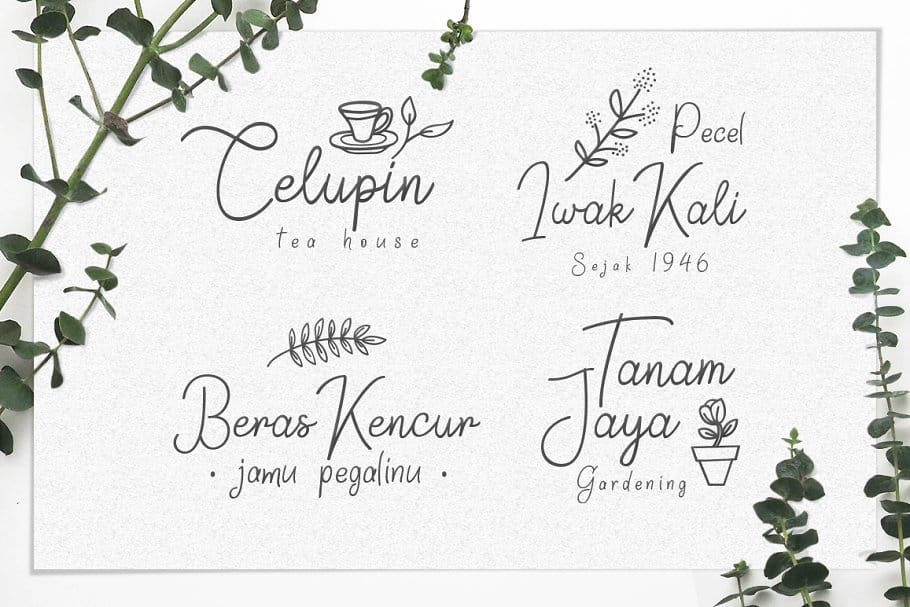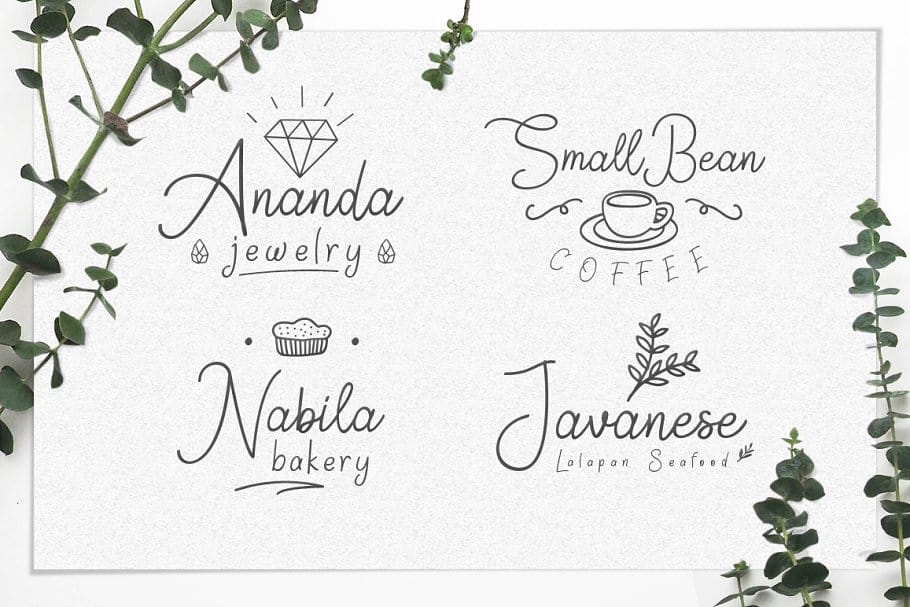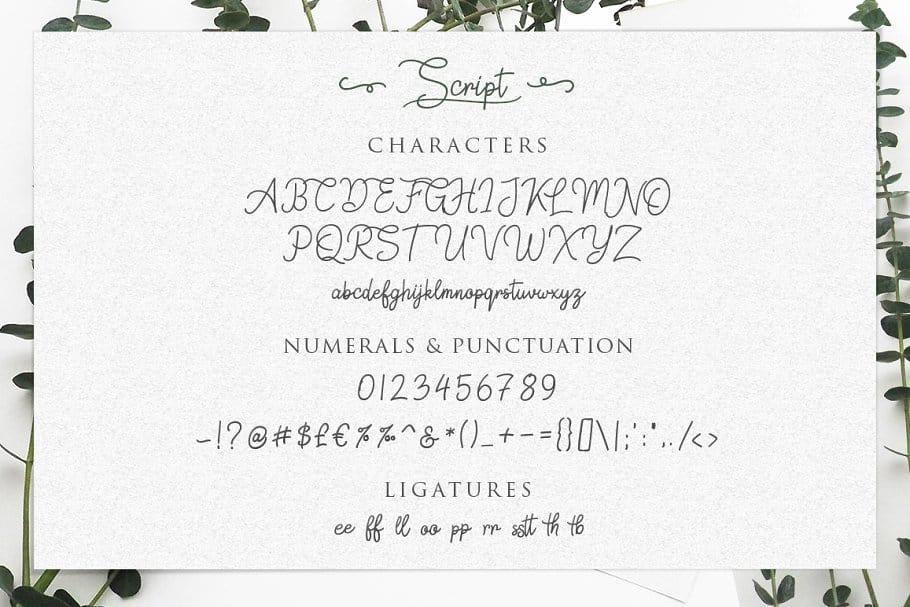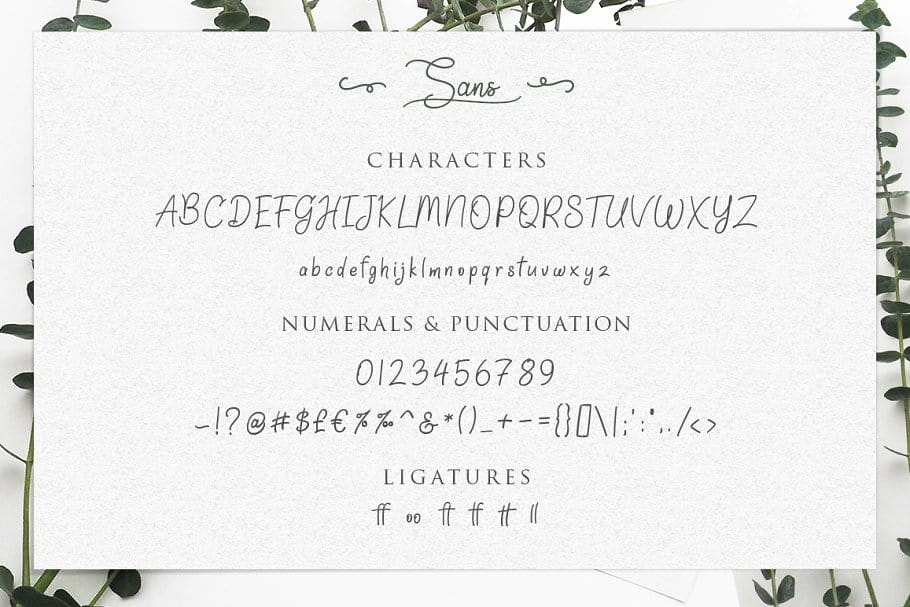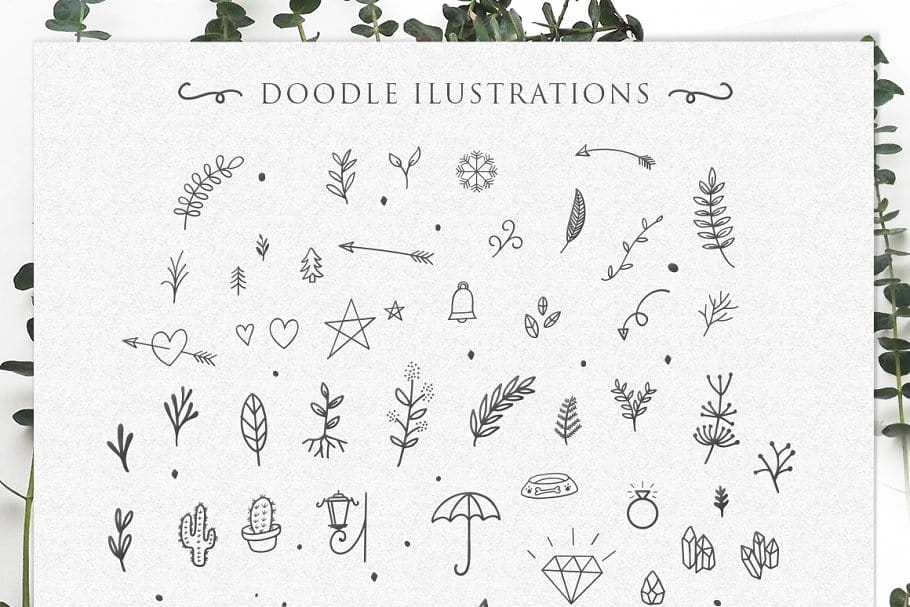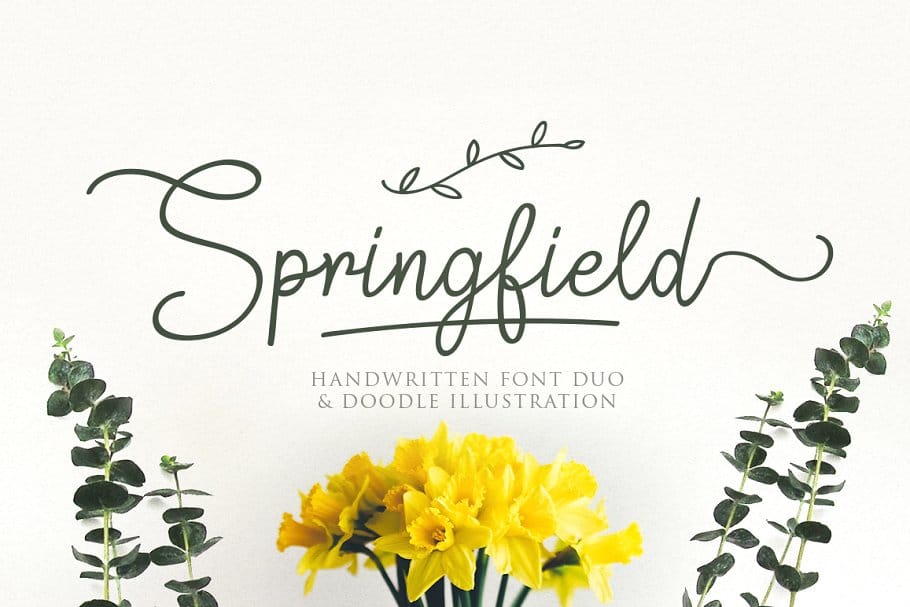
Springfield | Fontduo + Extras font chữ hoàn toàn mới với một bộ Hình minh họa doodle miễn phí tiện dụng. Cho phép bạn tạo kiểu chữ thủ công đẹp mắt ngay lập tức. Với 2 font chữ khác nhau và hình minh họa doodle vui nhộn.
Springfield hoàn hảo cho các dự án xây dựng thương hiệu, logo, poster, bao bì sản phẩm, typo, thiết kế áo phông hoặc bất kỳ thiết kế nào.
- Springfield Script – Font chữ script.
- Springfield Sans – Font chữ Sans.
- Springfield Swash – Bao gồm 20 swash vẽ tay với định dạng font chữ.
- Hình minh họa Doodle – Hơn 80 hình minh họa doodle tiện dụng.
Tất cả các font chữ có chứa ký tự viết hoa và viết thường, chữ số và một loạt các dấu câu. Với định dạng otf và ttf. Và hình minh họa doodle với định dạng ai và eps.